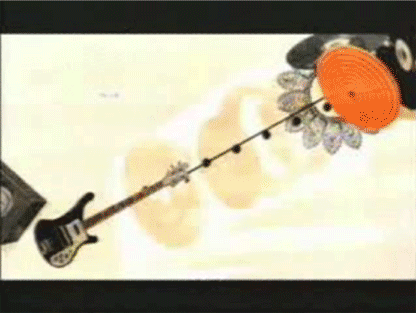
Toujours dans le même registre mais cette fois c’est Franz Ferdinand qui s’y est collé. Si qq peut me renseigner sur l’équipe des designers qui ont conçu ce video-clip, j’en serais ravi ;-) On y trouve toutes les belles influences graphiques des affiches russes et des détournements BrodyFashion avec une intelligence et une sensibilité rare.